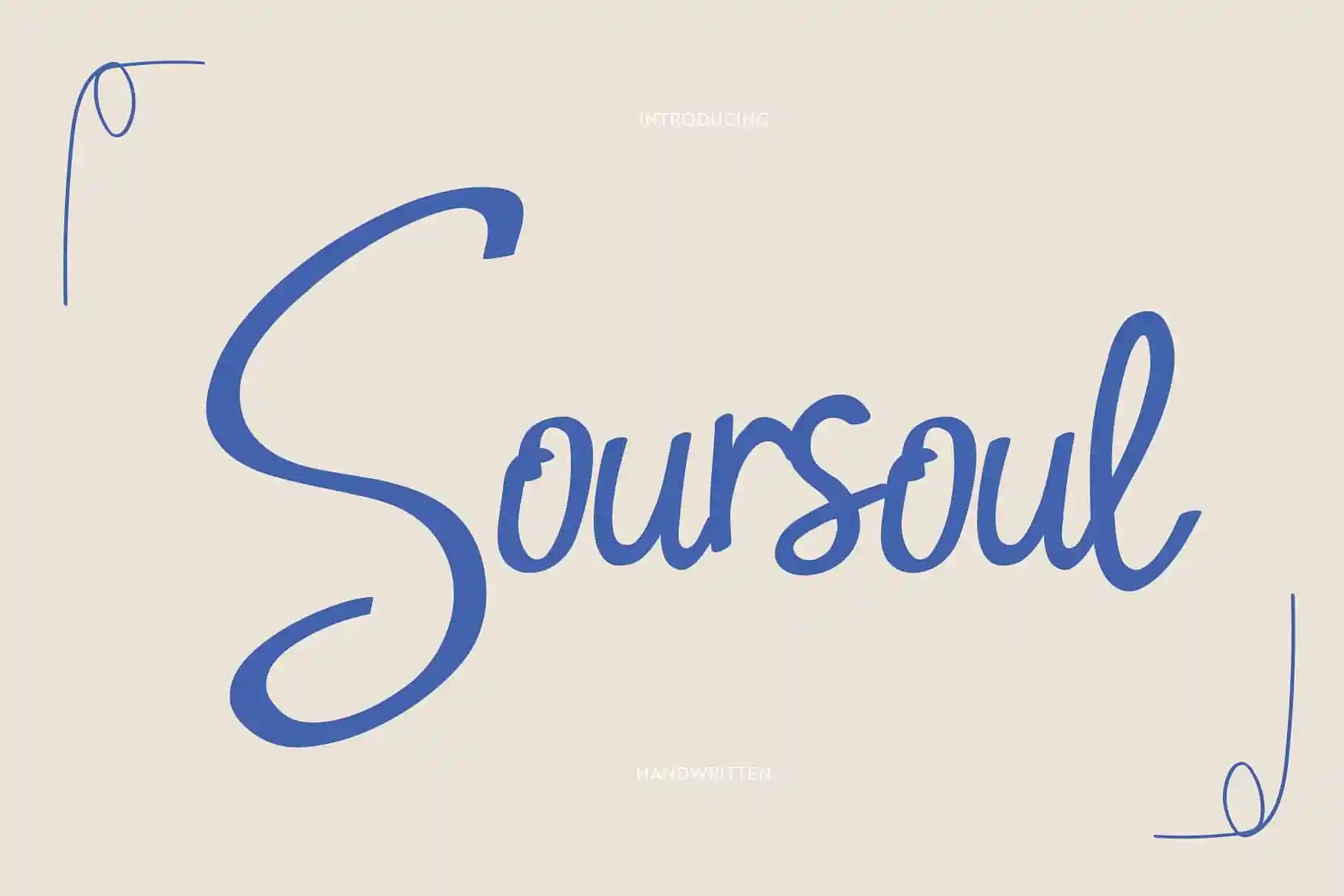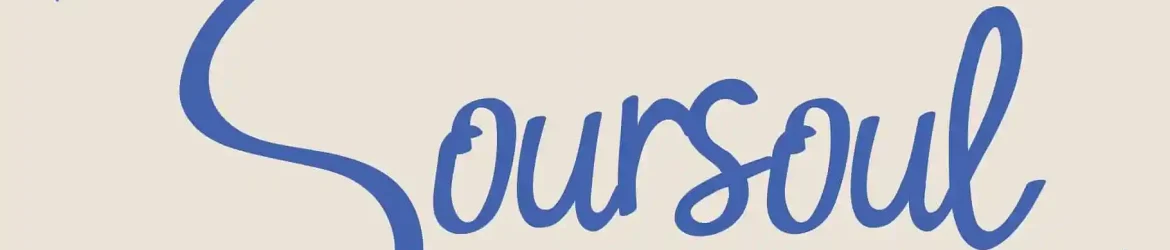
Soursoul Script Font – Download Grátis
Soursoul é uma fonte script que se apresenta como elegante e cheia de energia, embora sua origem seja aparentemente natural e casual. Criada por Hamilton na TypoBureau Studio, esta fonte representa um estilo autêntico da escrita a mão adaptado ao digital. Sua personalidade forte torna-a perfeitamente adequada para diversas finalidades gráficas, desde o uso em logotipos e marca até as embalagens de produtos, estampas ou cartões de visita. Não é de se esperar que ela se destaque apenas entre os clientes mais formais – sua presença poderosa transmite uma alegria leve e cheia de vida. Sua versatilidade e estilo único fazem dela um recurso valioso para qualquer designer buscando adicionar um toque especial aos seus projetos.